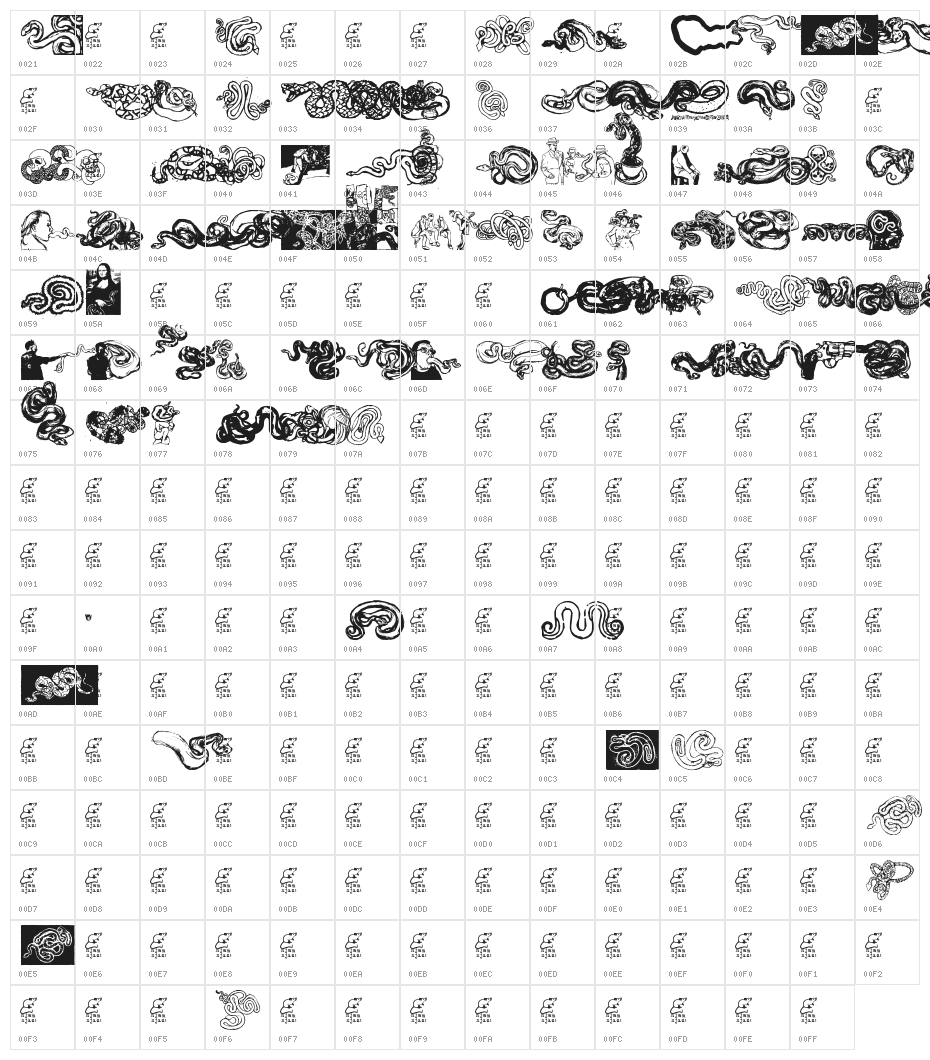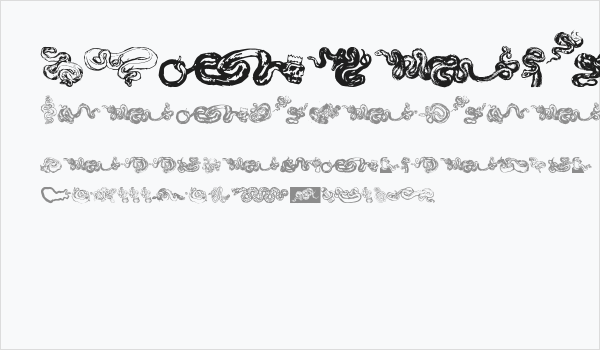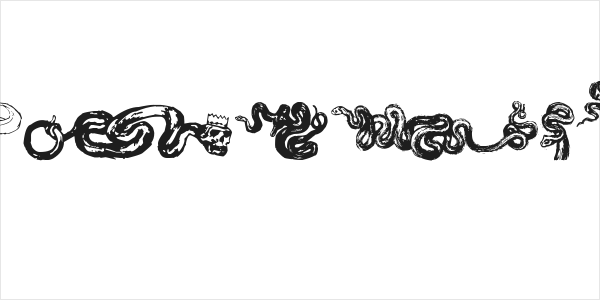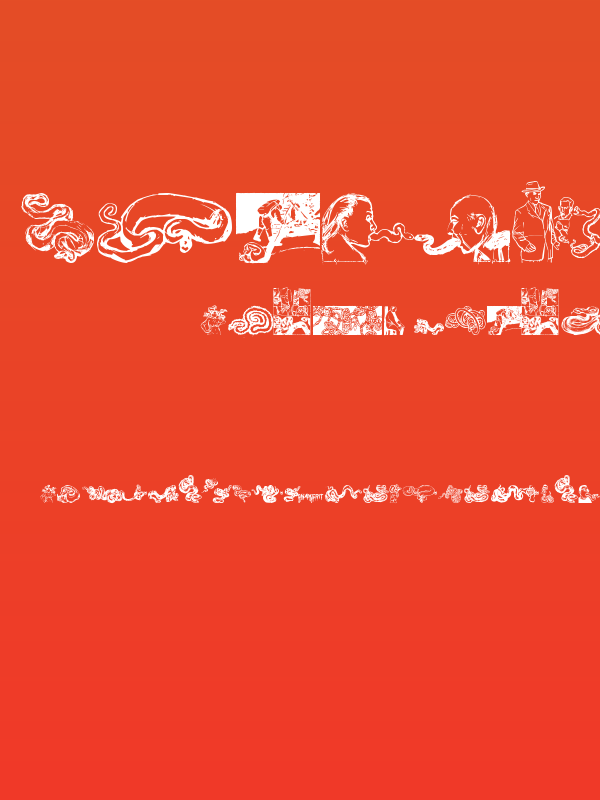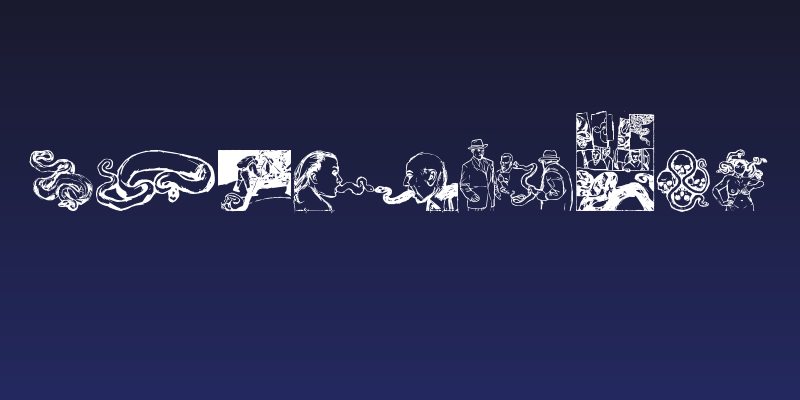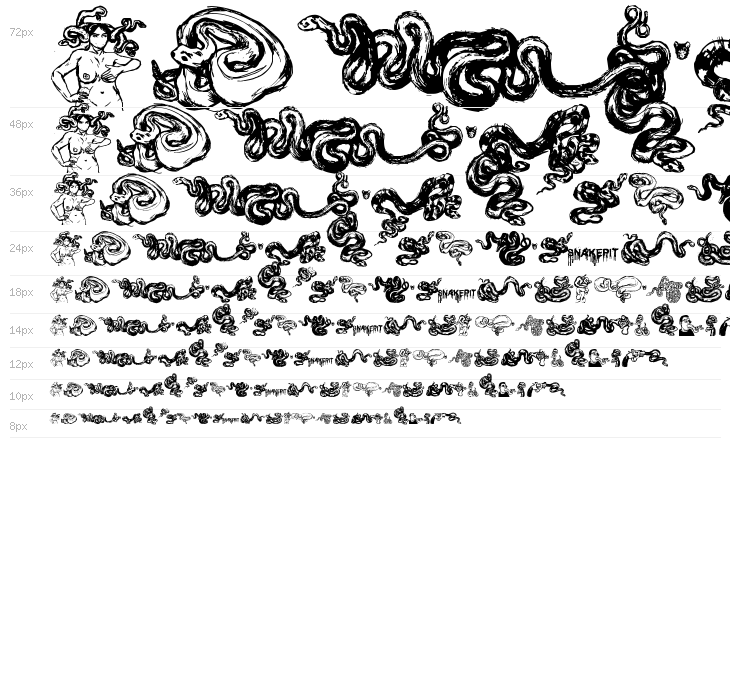
Snakepit Font
| Anwendungsfall | Logos, Posters, Themed Events |
| Vorgeschlagene Projekte | Ideal for themed event posters, fantasy book covers, or any project requiring a bold, artistic statement. |